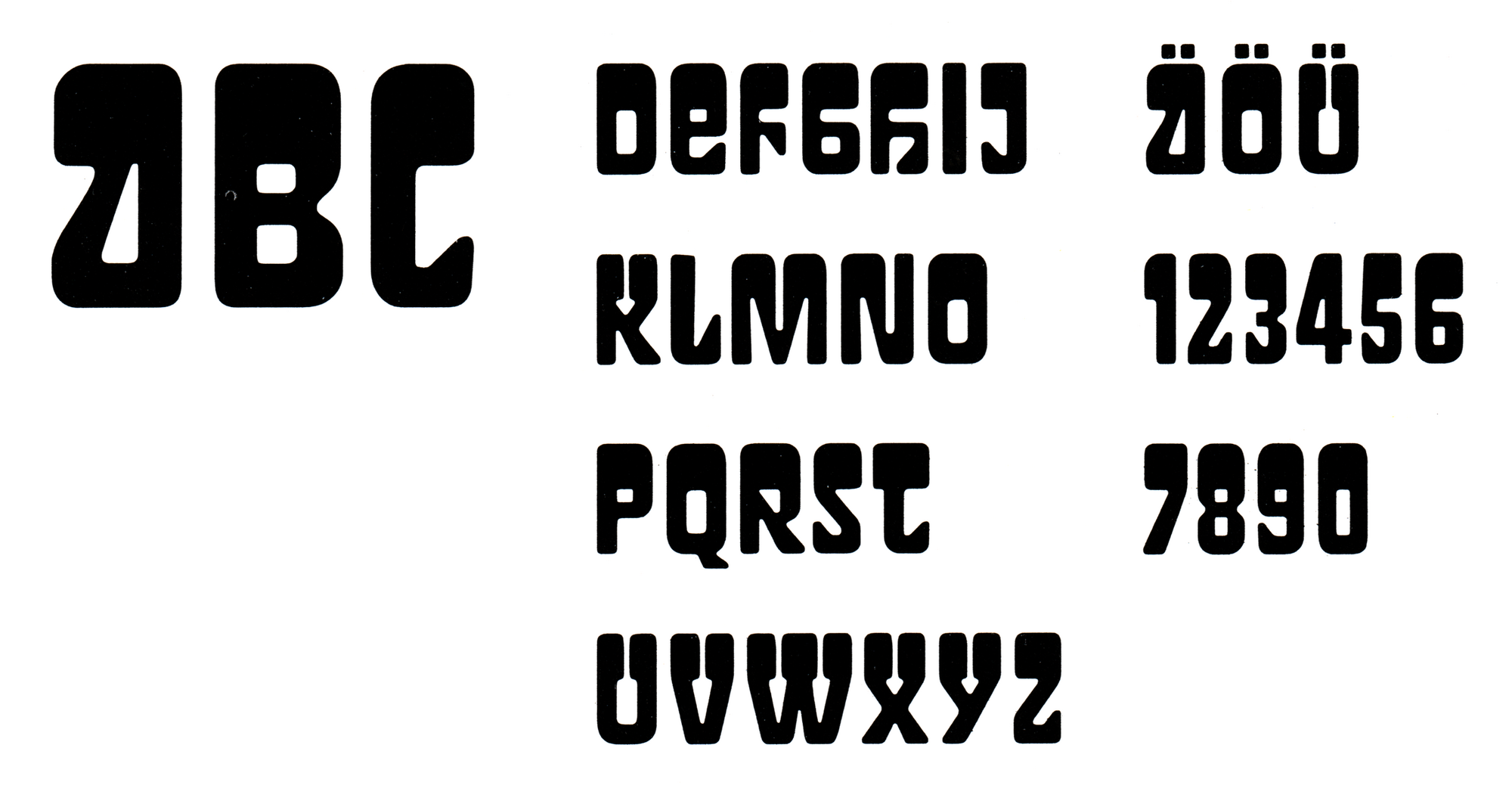
Mit der Zyklop errang Fritz Kossack bei einem Ideenwettbewerb für neue Auszeichnungsschriften (1985) den 3. Platz. Die Schrift wurde in der Folge zu einer Fotosatzschrift bei Typoart ausgebaut.
Eine digitale Version auf Basis der Originaldaten wurde von Elsner+Flake angeboten.